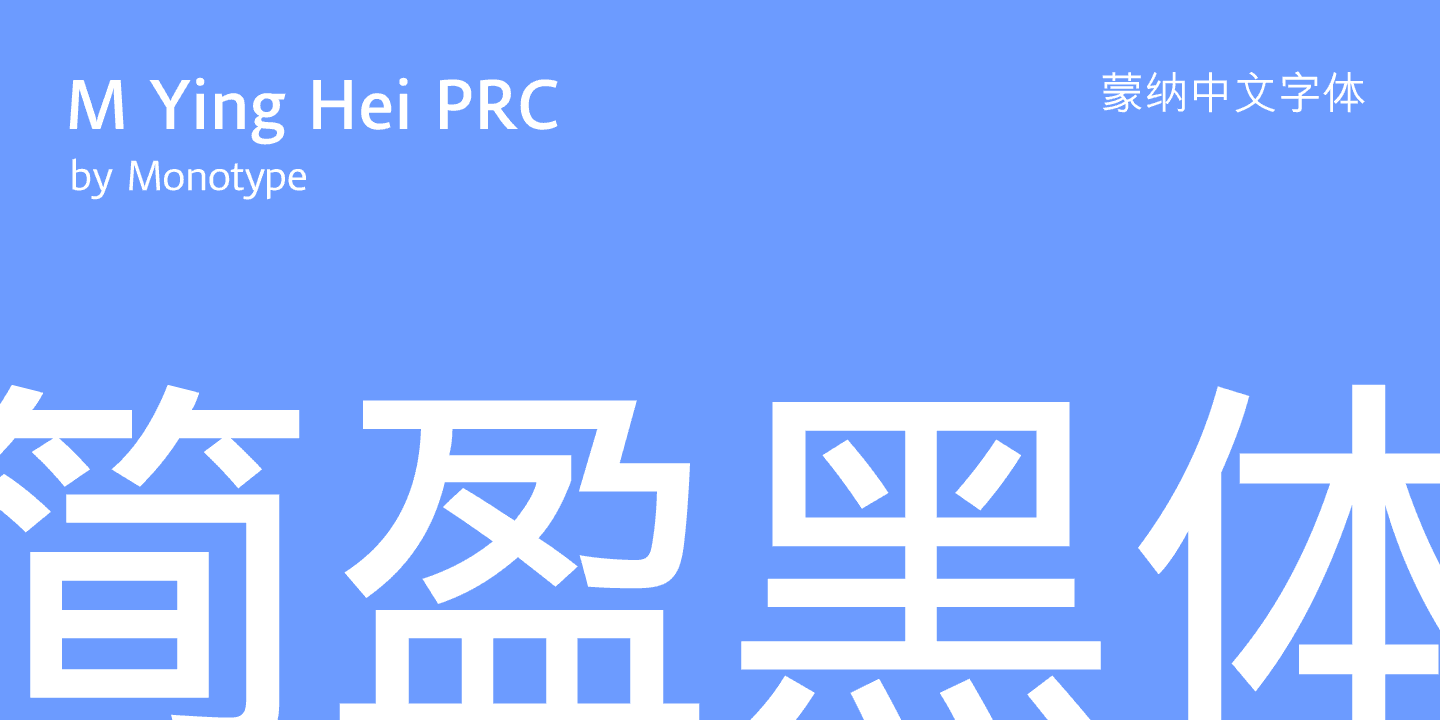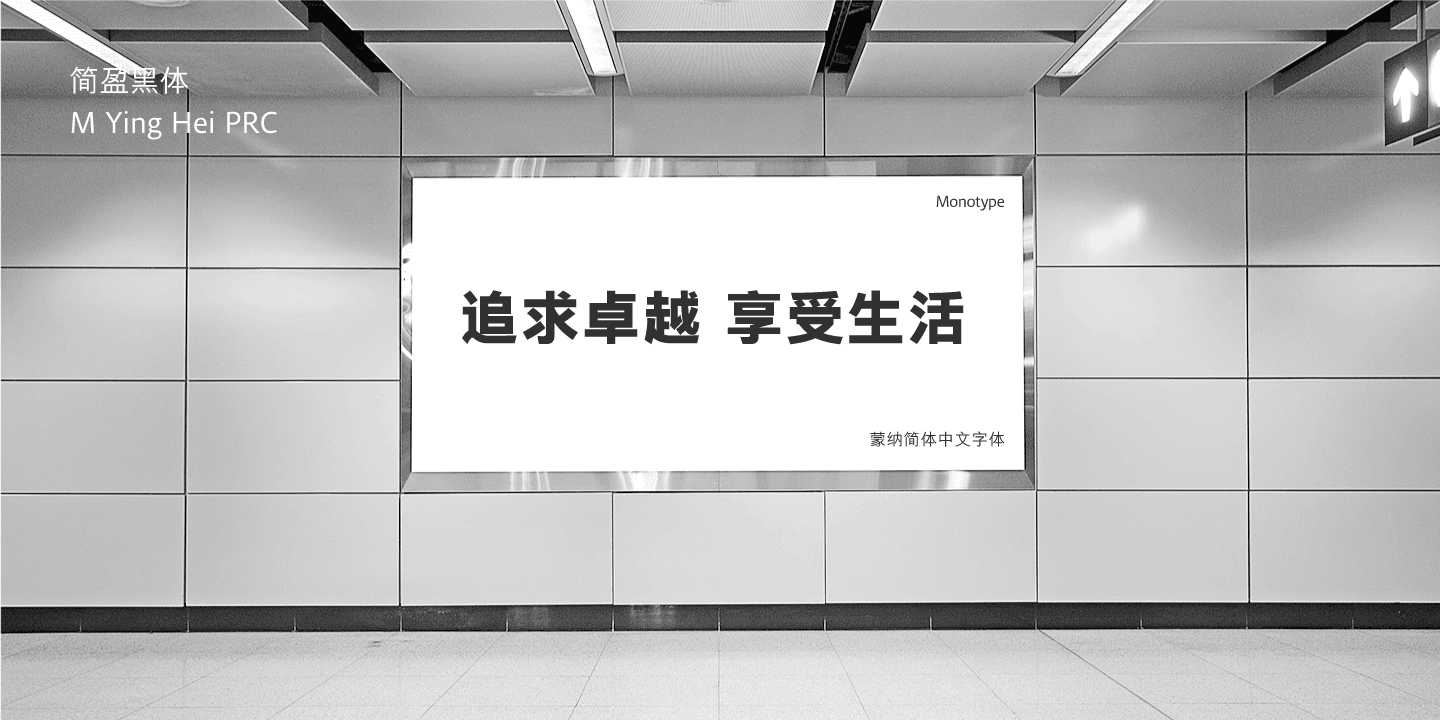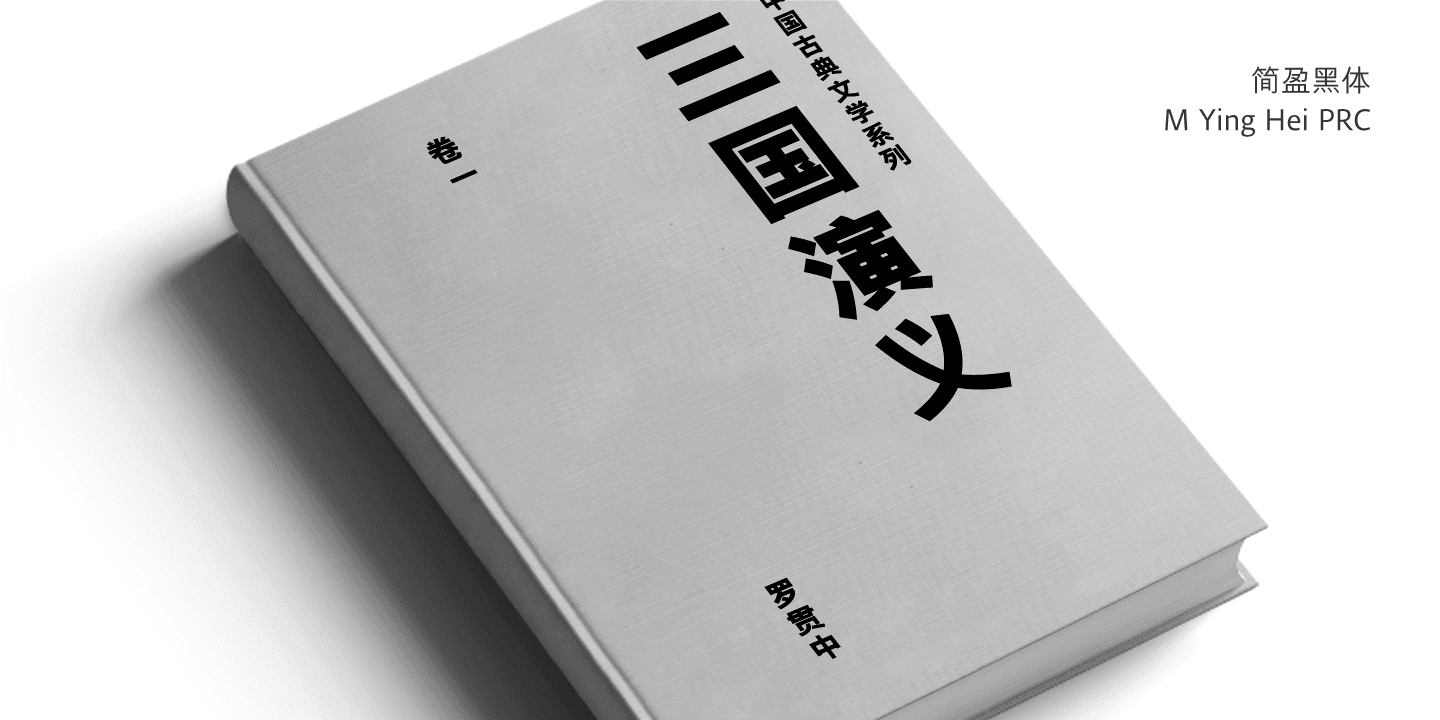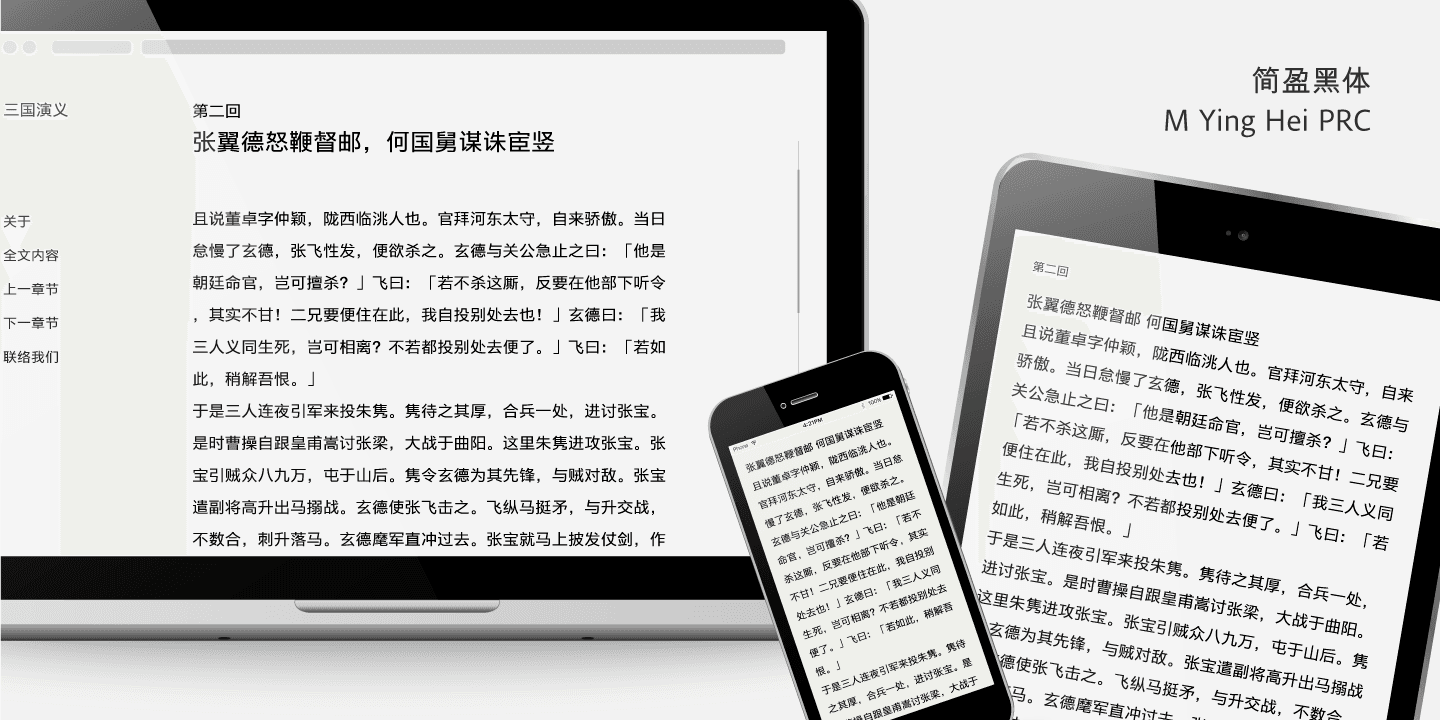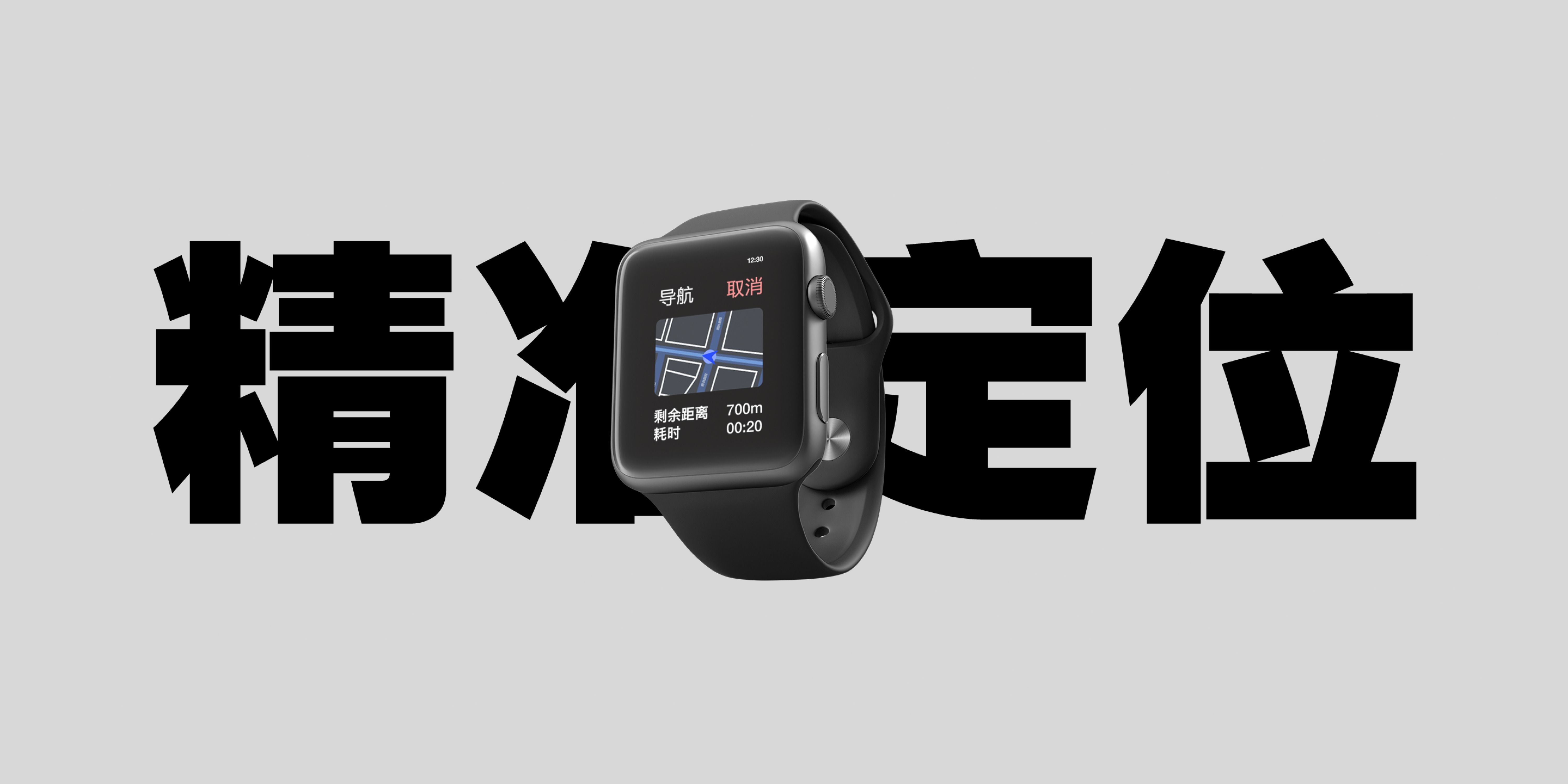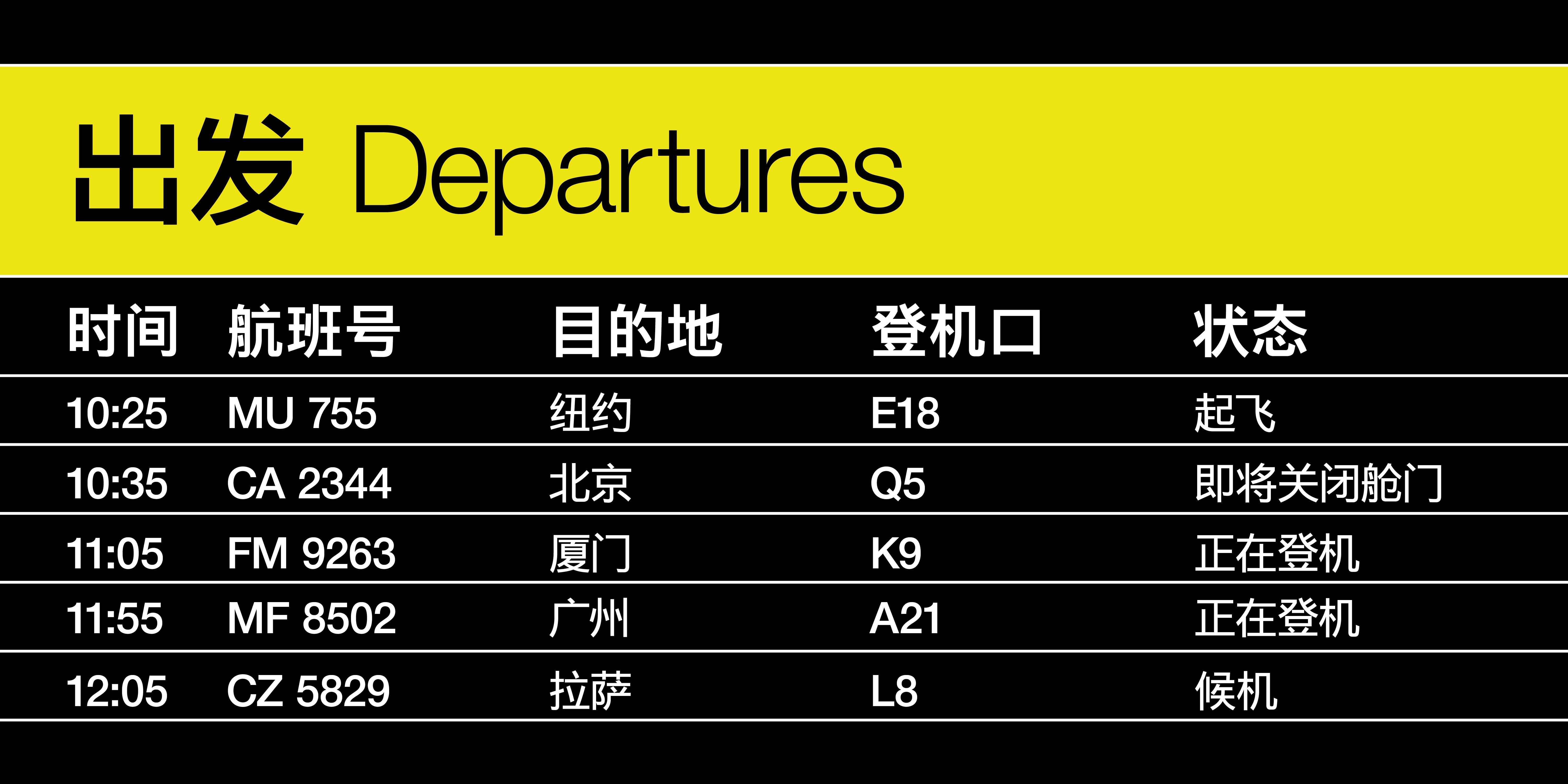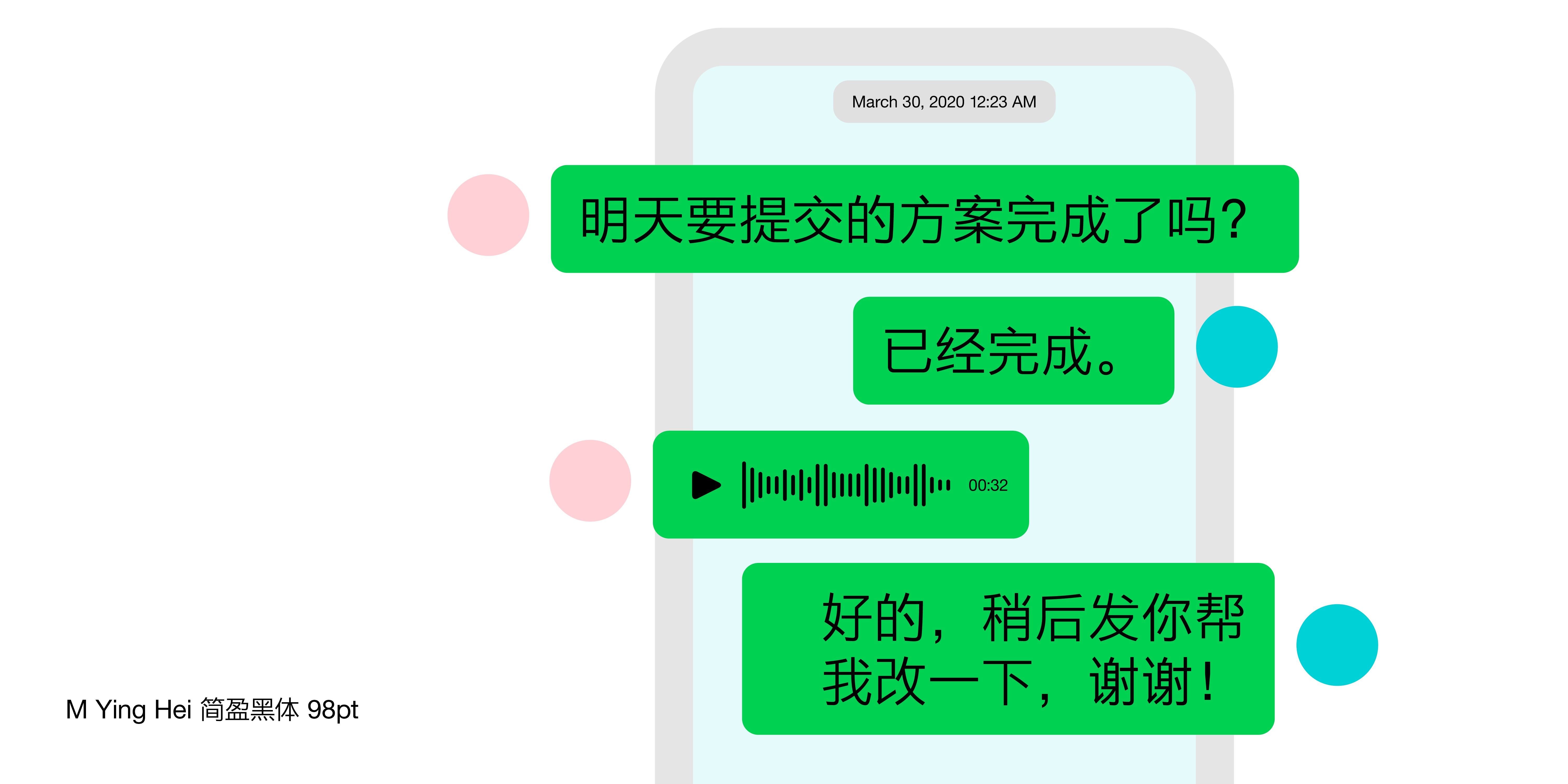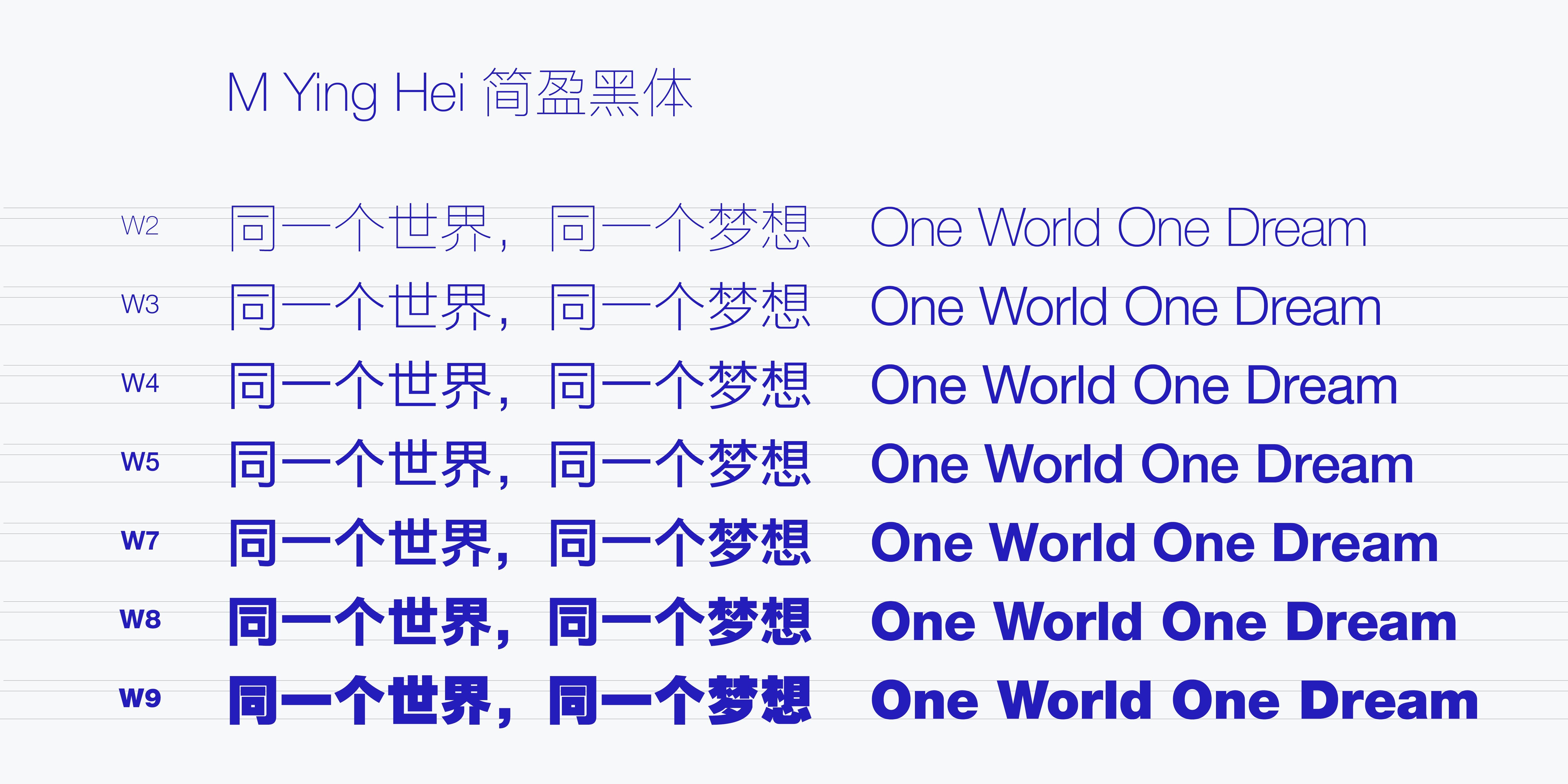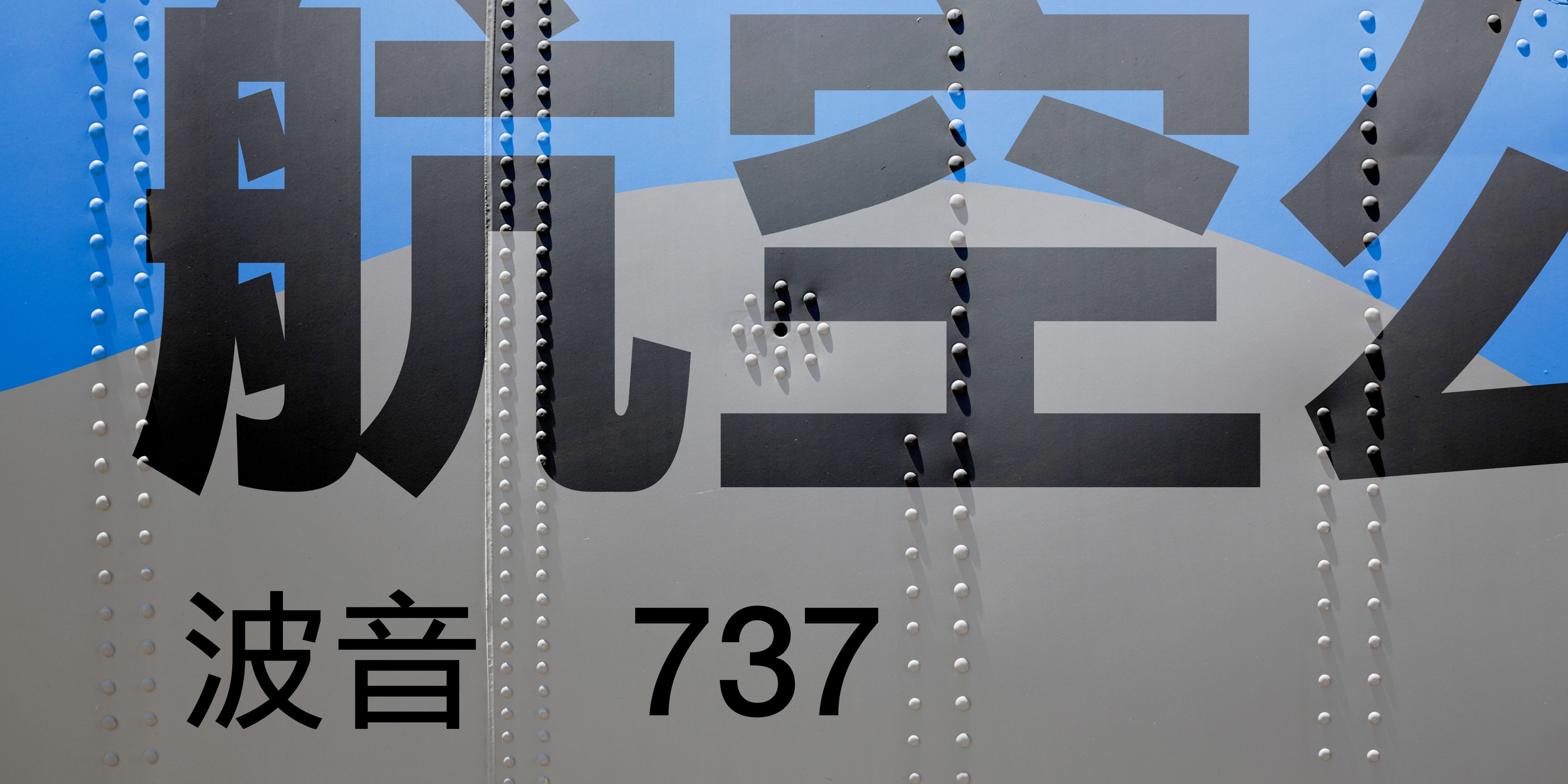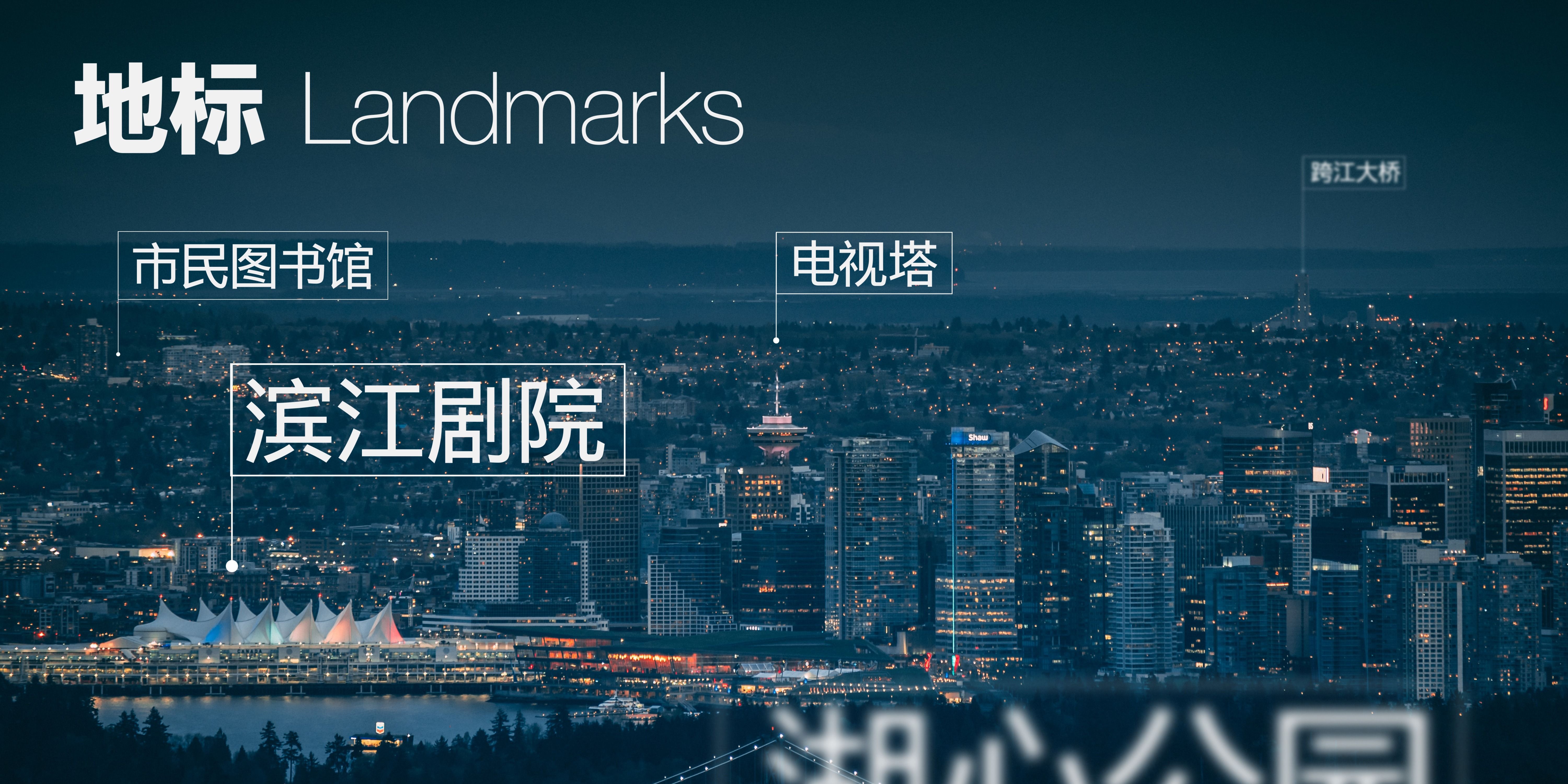
M Ying Hei PRC
디지털 시대를 위한 서체
Monotype
모노타입의 M Ying Hei PRC체는 기존 ‘모노타입 흑체’를 기반으로, 디지털 환경과 작은 화면에서도 뛰어난 가독성과 현대적인 이미지를 제공하도록 설계된 중국어 산세리프 서체입니다. 넓은 중궁과 다양한 웨이트로 다양한 브랜드 서체와 잘 어울리며, 빠른 정보 전달에 최적화되어 있습니다.